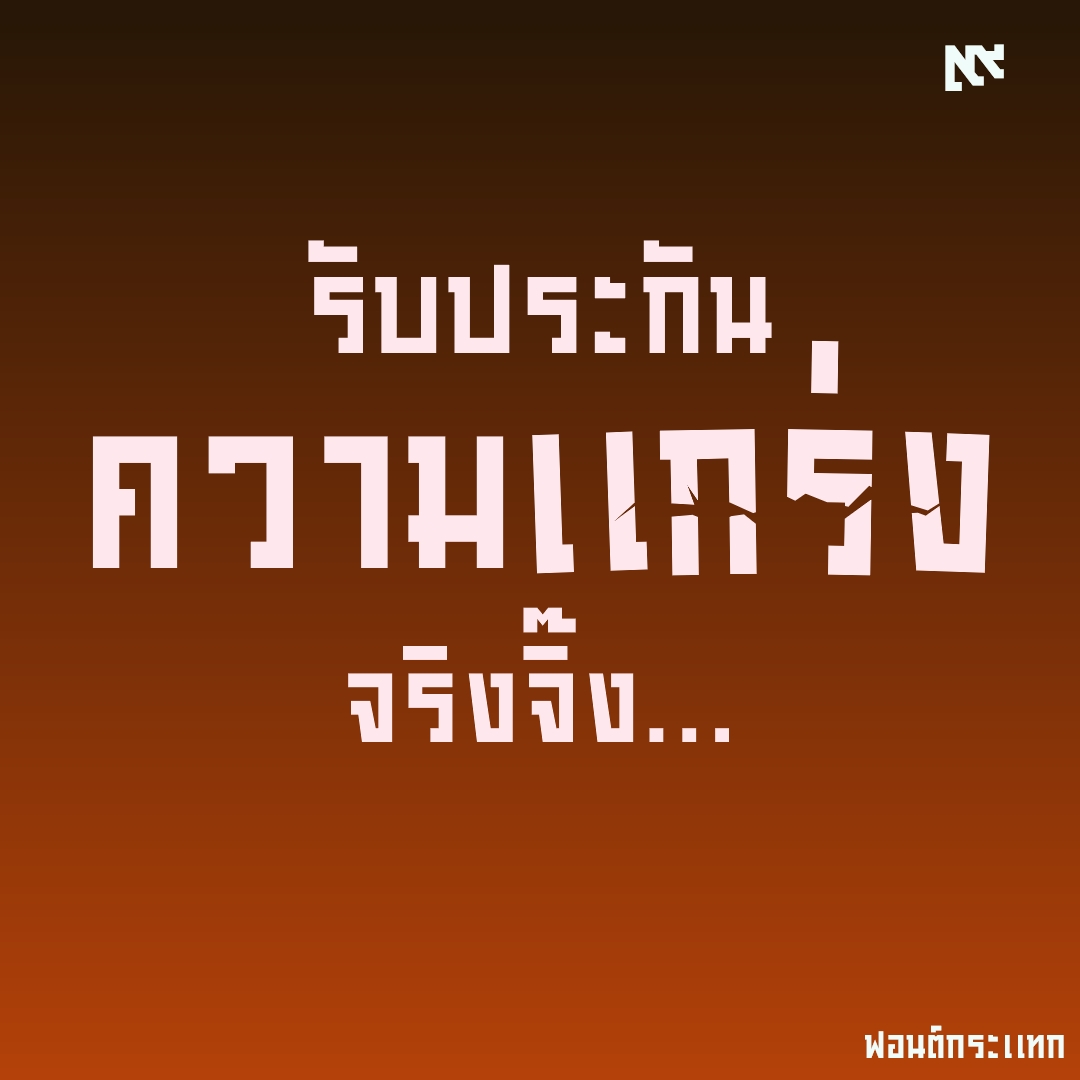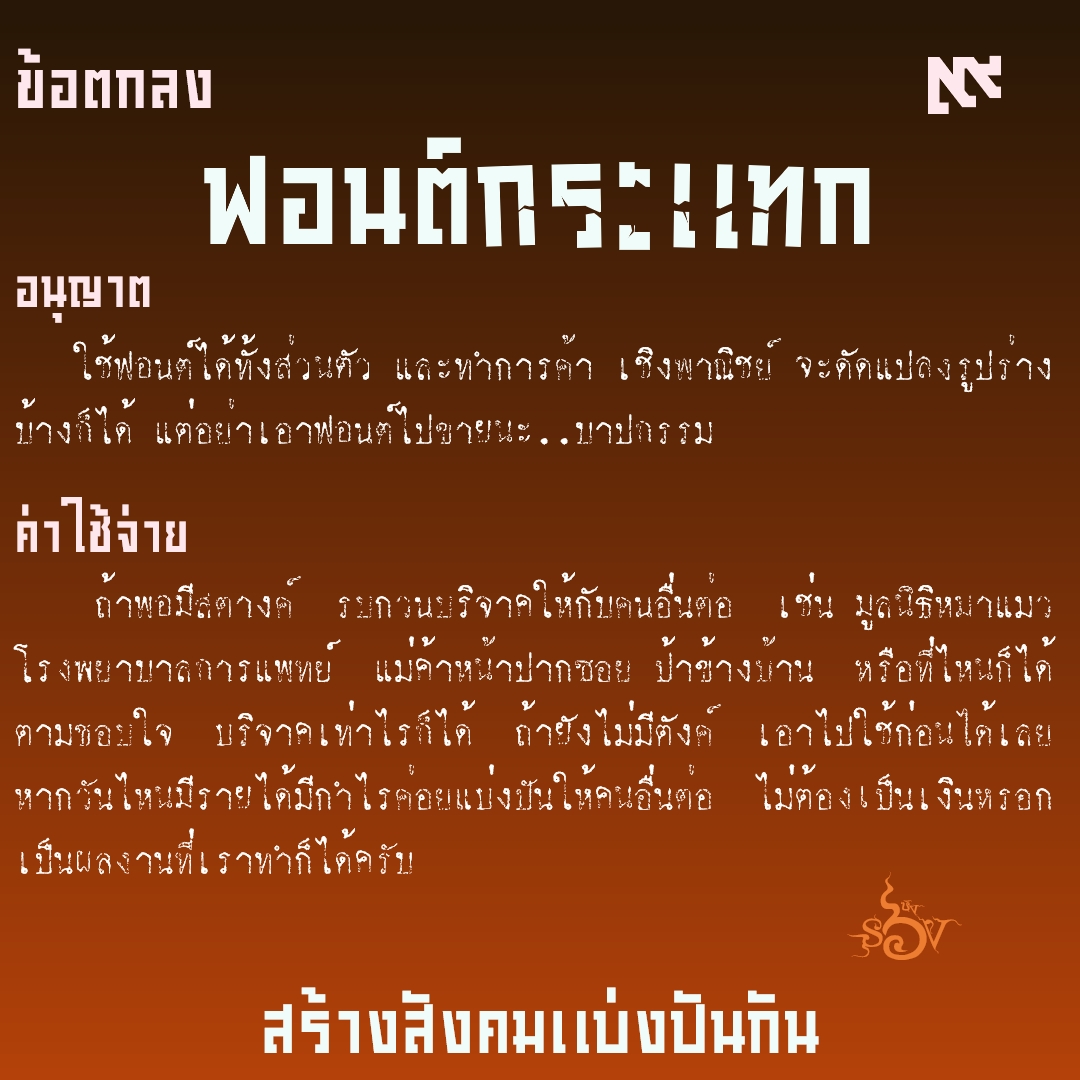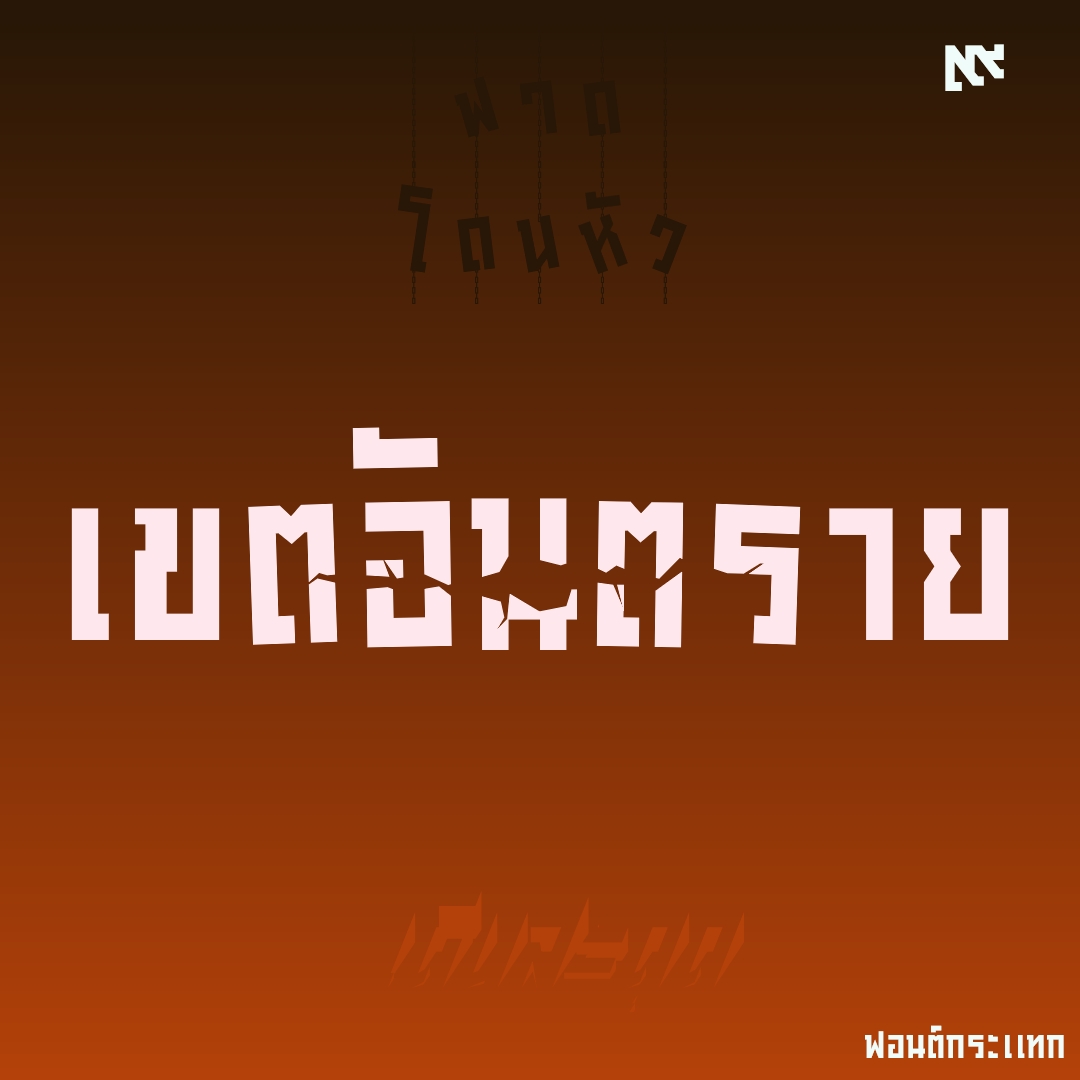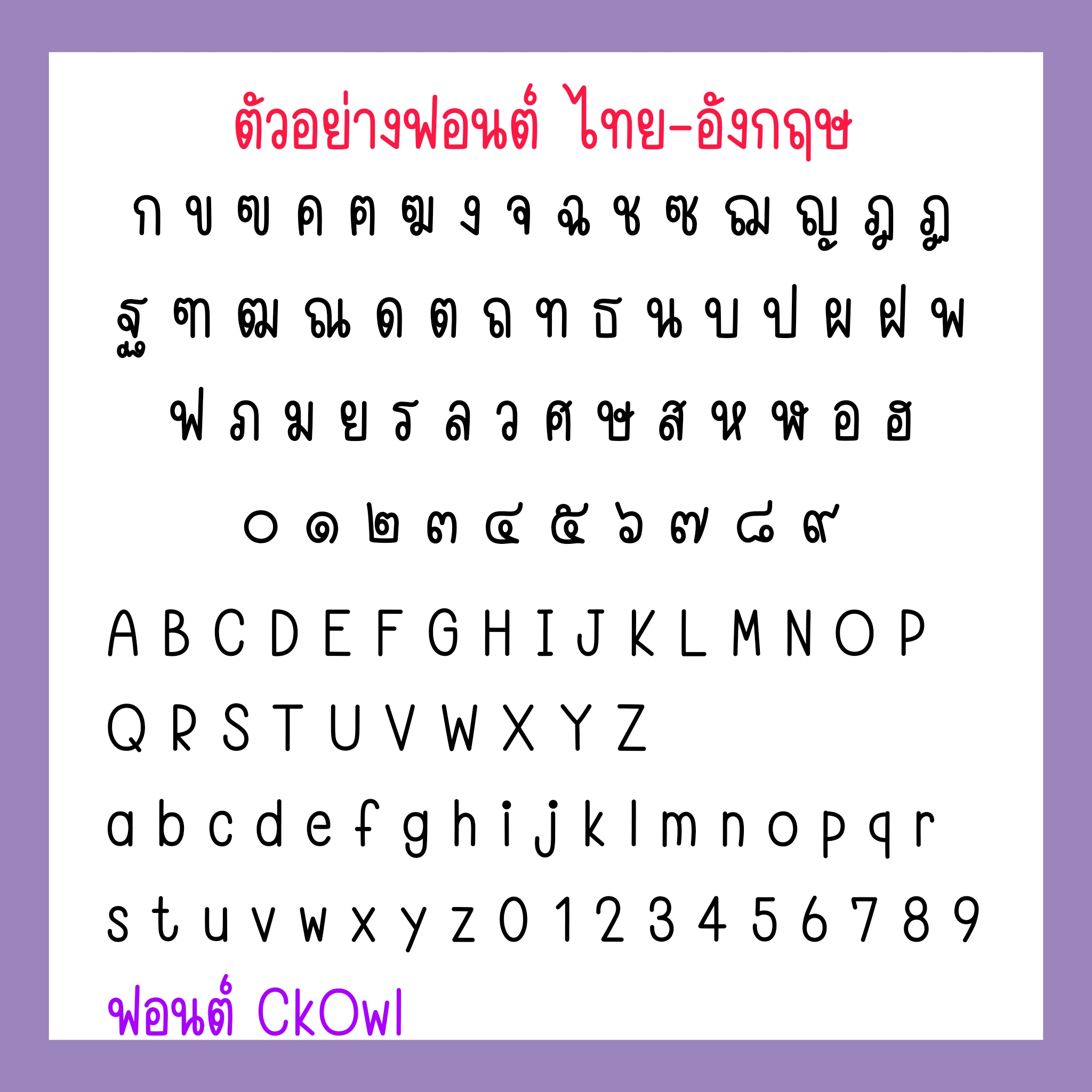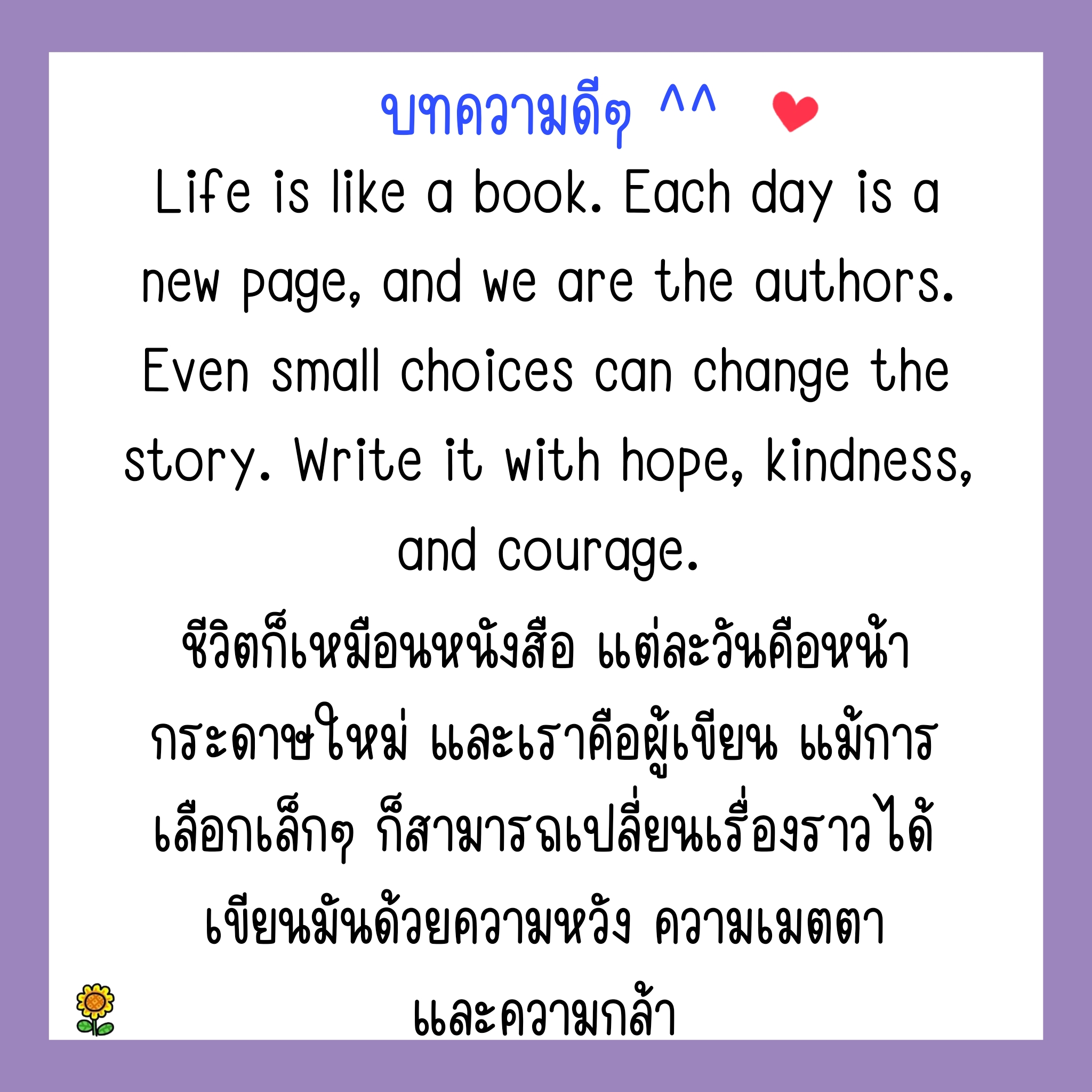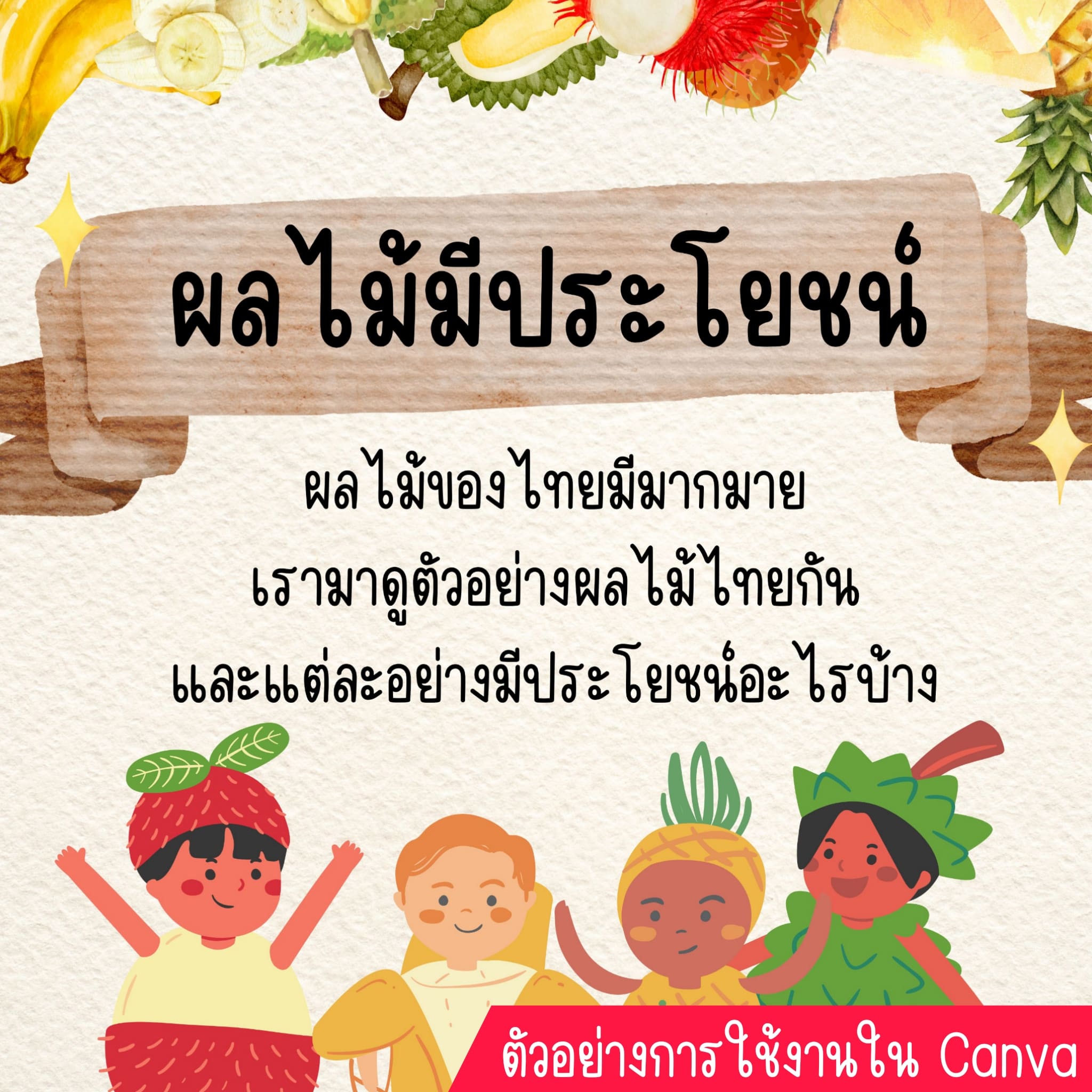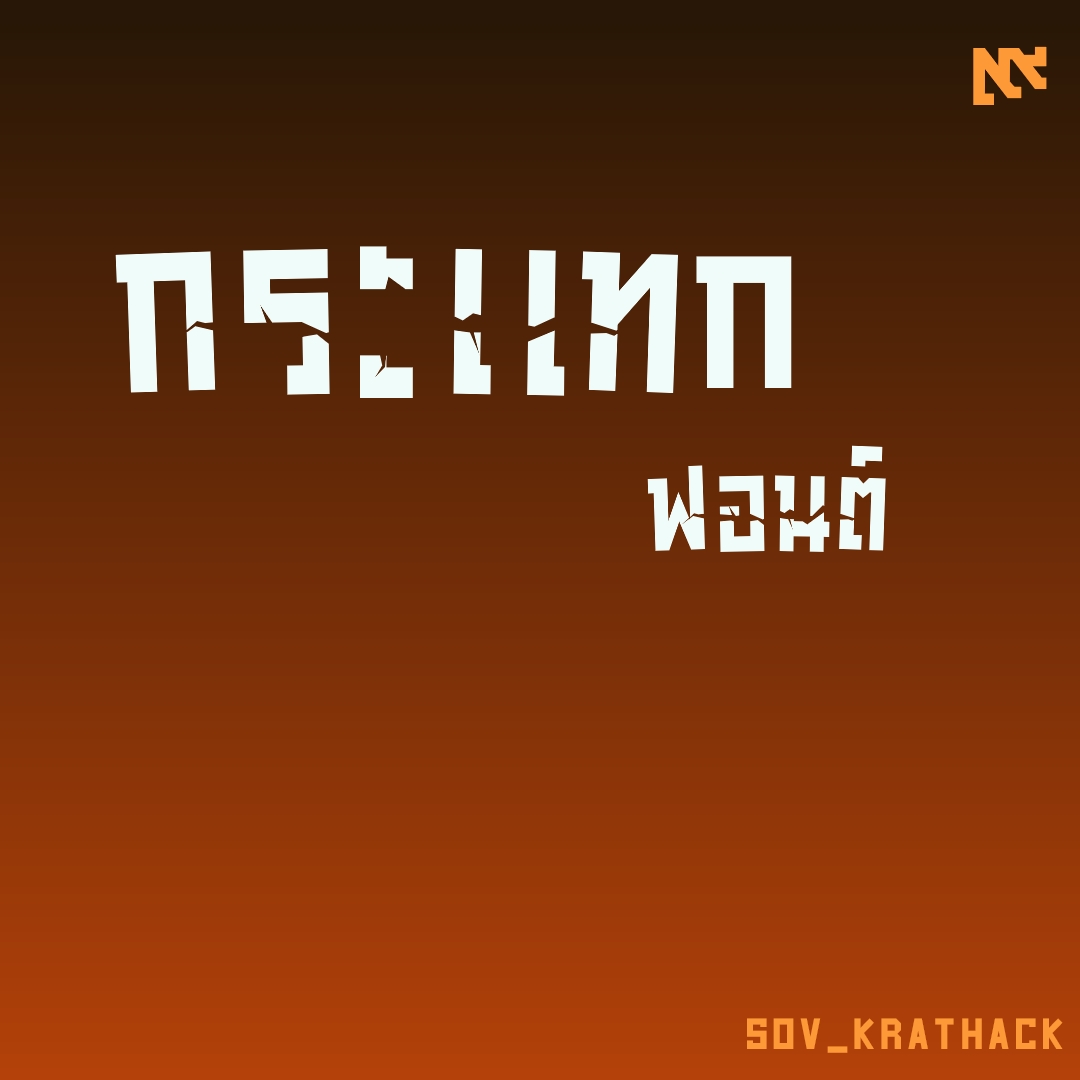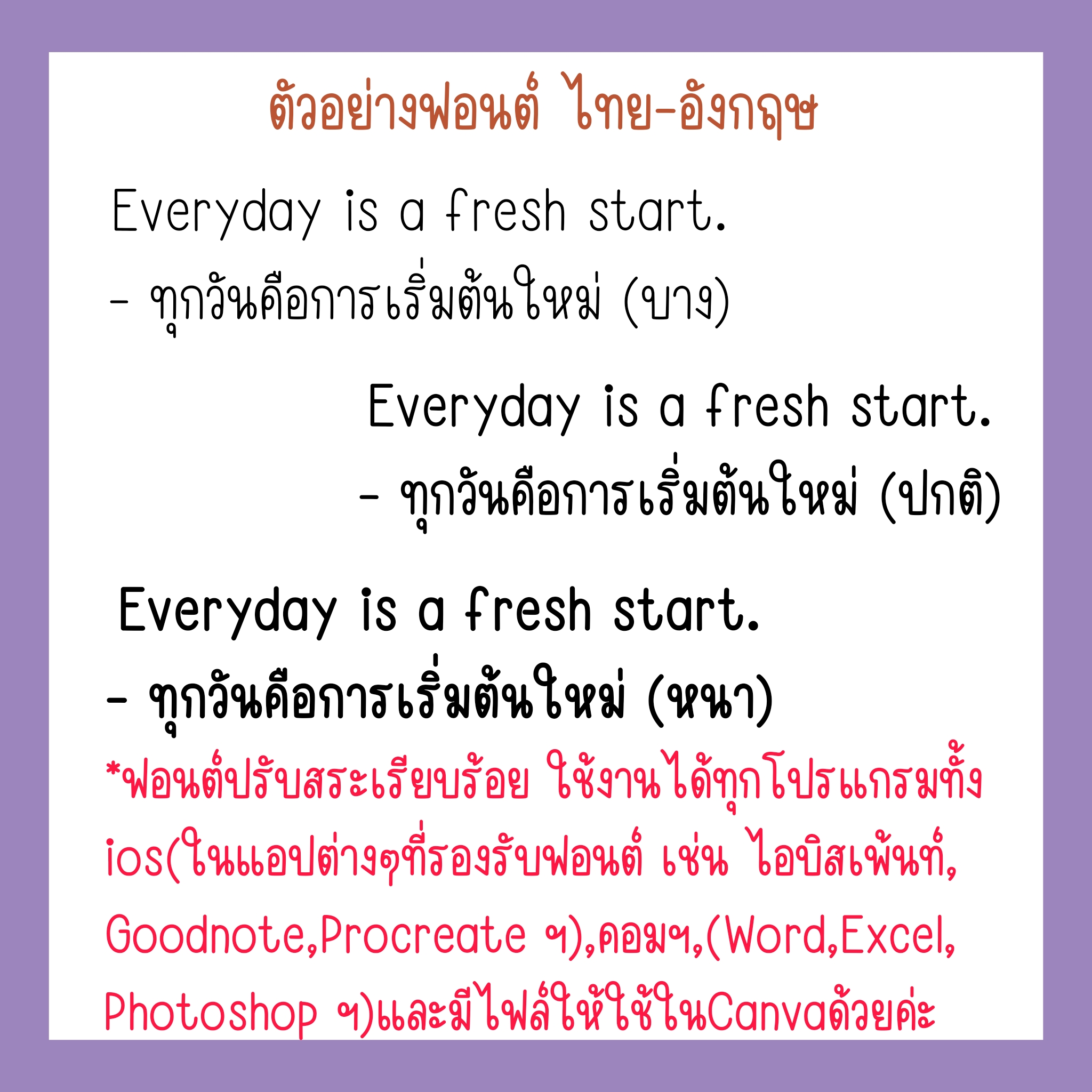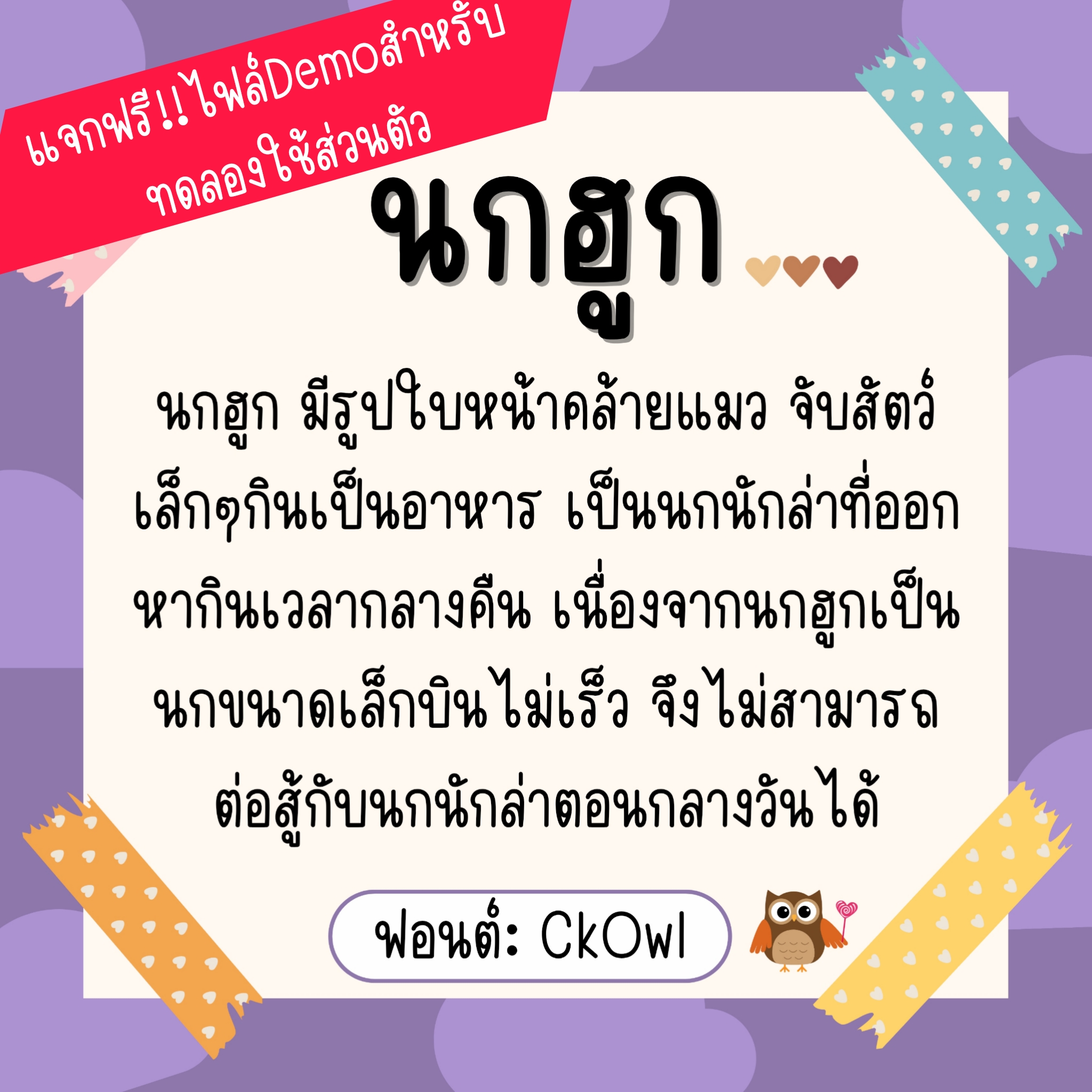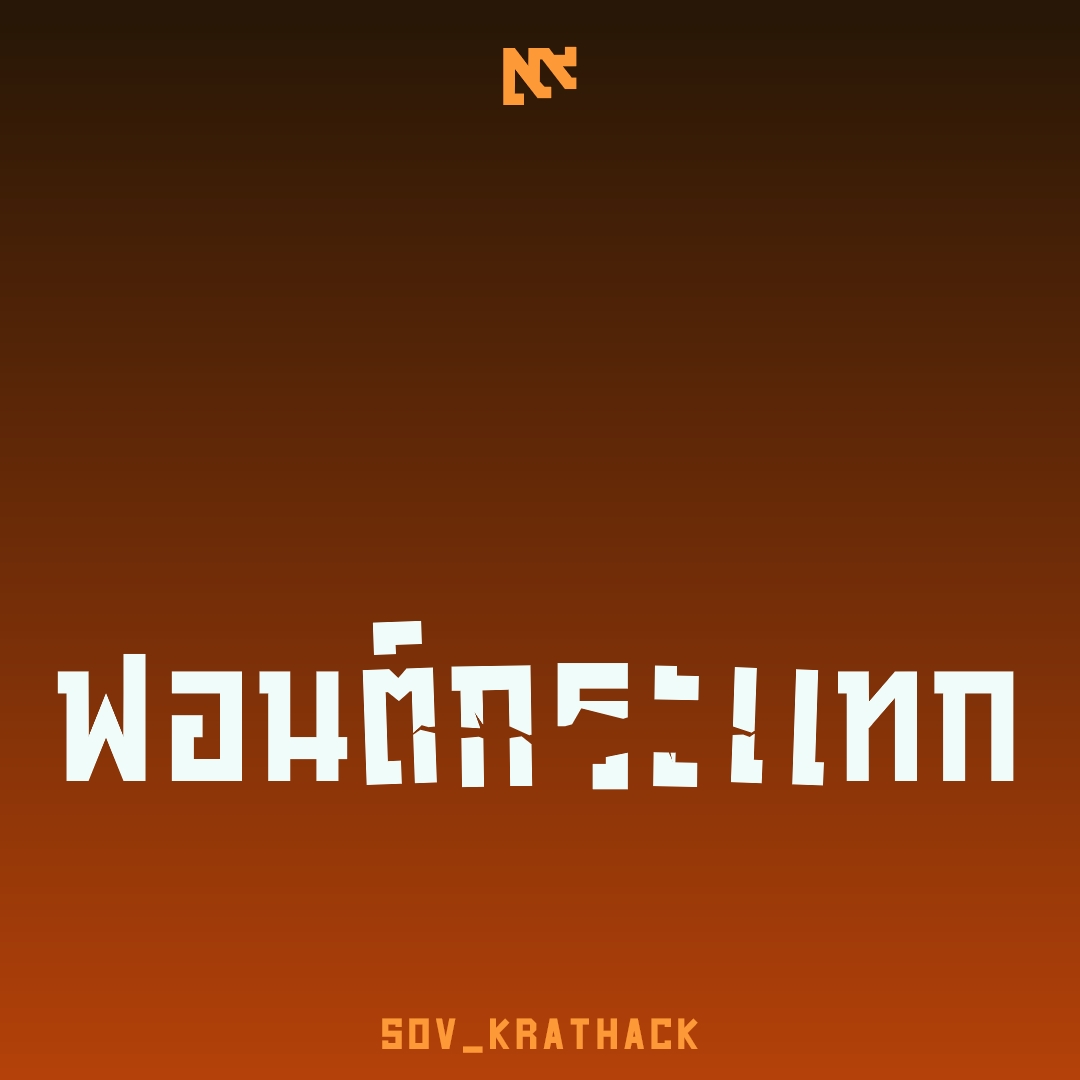
- ฟอนต์ CkOwl ฟอนต์ลายมือแนวน่ารัก อ่านง่าย หัวยาว ตัวเพรียวๆค่ะ
ชื่อฟอนต์ : กระแทก
ฟอนต์กระแทก ใช้ ฯฯ หน้าอักษรที่อยากให้ถูกกระแทก แตกได้ 1-5 ตัวอักษร
ชื่อฟอนต์ : ฟิ้ววววว
ฟอนต์ตัวนี้ให้นึกภาพว่า เอาแปรงทาสีร่างตัวอักษรเสร็จ แล้วเอากิ่งไม้เล็กๆ ลากขวาง..ฟิ้ววววว (ตัวปรกติฟิ้วววววไปขวา ตัวหนาฟิ้วววววไปซ้าย)
ฟอนต์
(BF )
ฟอนต์มะเขือเทศ [RDTomato]
ชื่อฟอนต์ : บลัดดี้แมรี่  (GMCctBloodyMary)
ไฟล์ Demo มีตำหนิ น้ำหนักไม่เท่ากัน